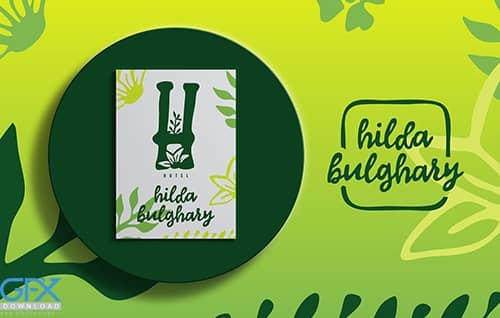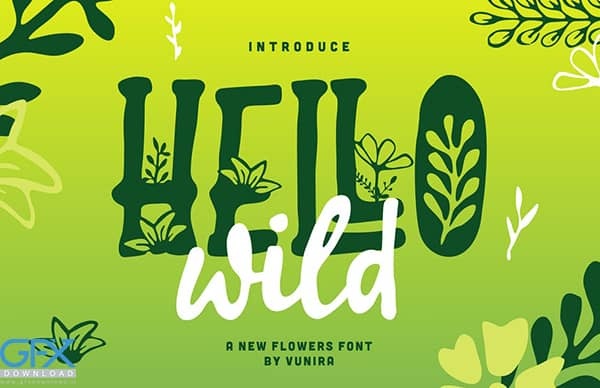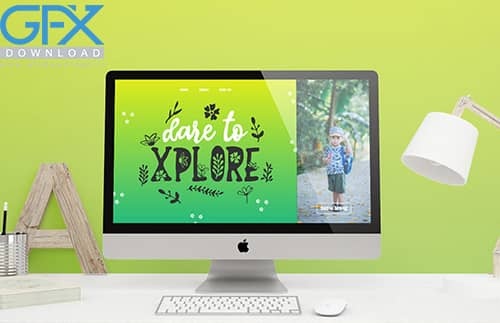
دانلود فونت رایگان گل و گیاه Flowers Font
دانلود فونت رایگان گل دار
دانلود رایگان فونت گل دار با طرح گل و گیاه Flowers Font
این فونت زیبا با سبک خوشنویسی ، بسیار زیبا قابل استفاده در دعوت نامه ها مانند کارت تبریک ، برند تجاری ، کارت ویزیت ، نقل قول ها ، پوستر و موارد دیگر است. با دانلود فونت رایگان گل و گیاه Flowers Font می توانید از آنها در طرح های گرافیکی خود استفاده کنید. یک فونت تزئینی بسیار زیبا و منحصر بفرد که می‌توانید از آن در انجام طراحی‌های ویژه‌ای نظیر بهار، رویش، زندگی و طرحهایی که به نحوی با وجود زیبای گل در ارتباط هستند بهره بگیرید. به راحتی بعد از دانلود می توانید از آن ها در فتوشاپ،ورد،ایلستریتور و سایر نرم افزار های دیگر استفاده نمایید.
فونت گل و گیاه رایگان Flowers Font
این فونت رایگان مناسب برای طراحان و گرافیست های خوش ذوق است که می توانند از این مجموعه زیبای گل دار در طراحی پروژه های خود کمک بگیرند.
دانلود فونت گلدار Flowers Font